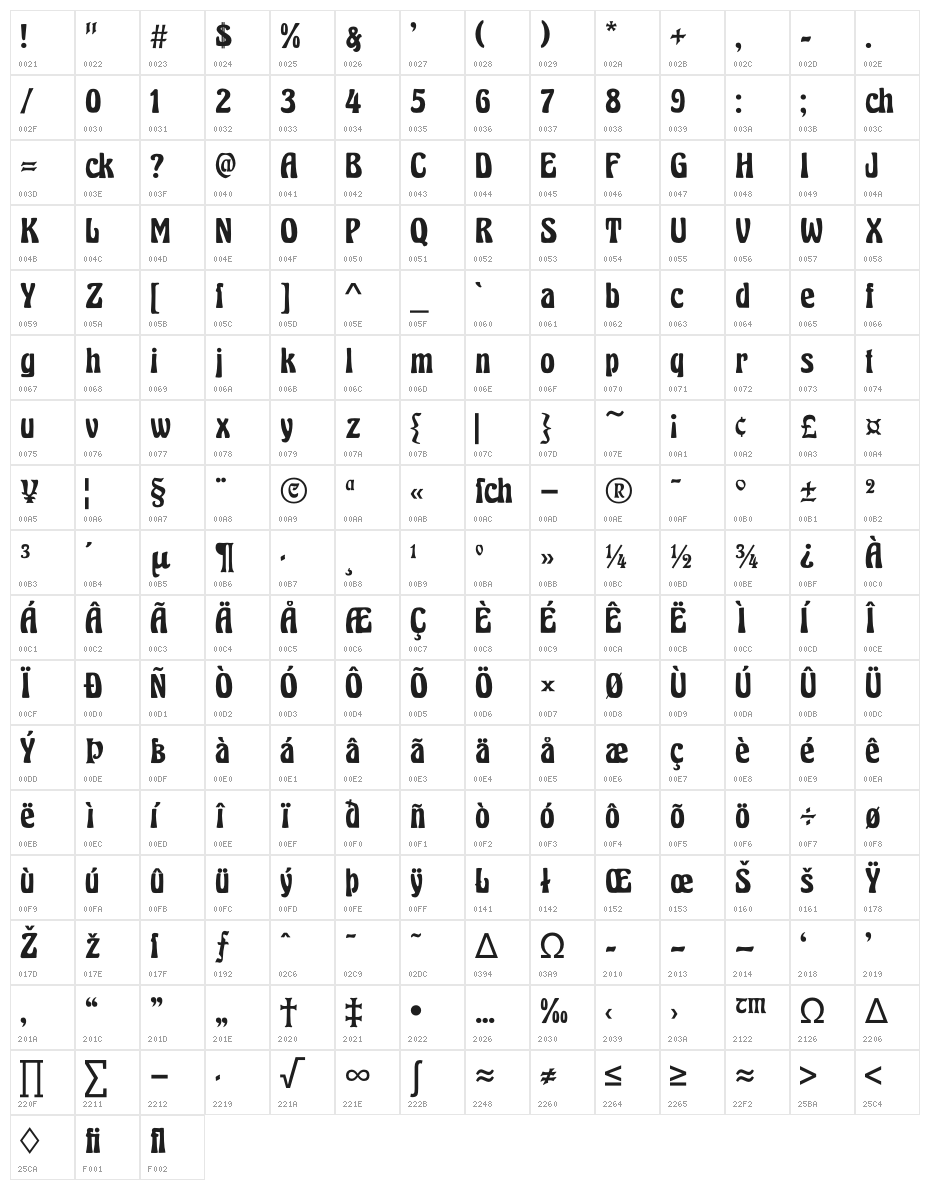
Herkules Font
| Gesamtstil | Playful, Whimsical |
| Anwendungsfall | Headlines, Posters, Branding |
| Vorgeschlagene Projekte | Ideal for children's books, playful branding, posters, and creative projects that require a bold and fun typeface. |